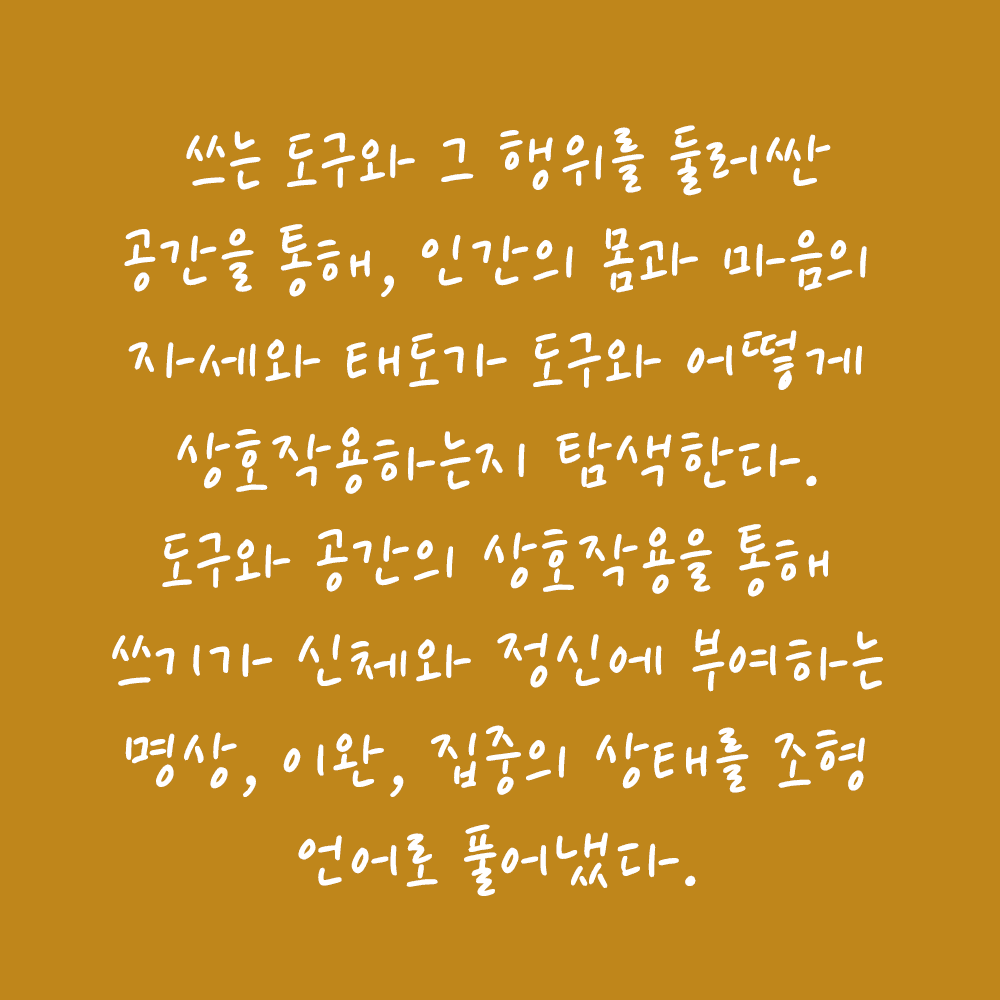
그리운X국한박 오춘기 김작가
GriunXHangeul OCHUNGI.KIM
그리운X국한박 오춘기 김작가 소개
제5회 한글실험프로젝트 《글(자)감(각): 쓰기와 도구》 The 5th Hangeul Design Project 《Senses of Writing: Tools & Perception》 전시기간: 2025.11.19.~2026.3.22. 전시장소: 문화역서울284 RTO 주최·주관: 국립한글박물관 이 손글씨 폰트는 국립한글박물관 제5회 한글실험프로젝트 《글(자)감(각): 쓰기와 도구》 전시 연계 이벤트를 통해 제작되었습니다. 손의 움직임과 쓰는 감각을 그대로 담아, 쓰기의 경험을 폰트로 확장합니다.